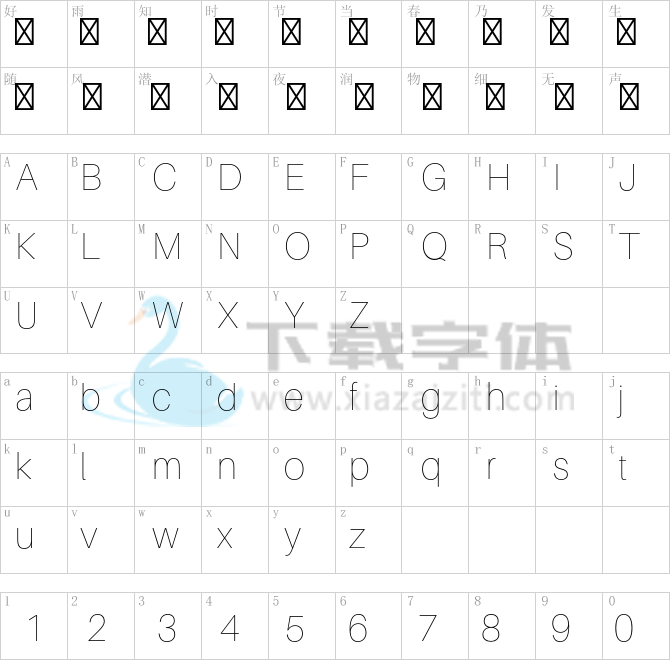
Aileron UltraLight.otf字体下载,这款字体结构工整、笔画清晰,兼顾美观与易读性,适用于标题、正文、海报、包装、LOGO 等多种场景。字形优雅稳定,风格百搭耐看,适配日常排版与创意设计,让文字呈现更舒适、更具质感。Aileron UltraLight.otf字体下载一笔一画,皆是细节,以均衡的比例、流畅的线条打造舒适视觉体验,字形端正大气,风格简约现代。无论是商业设计、品牌宣传还是日常排版,都能轻松驾驭,让文字更有格调与力量。Aileron UltraLight.otf字体下载字体下载。
Aileron UltraLight.otf图片展示
Aileron UltraLight.otf映射图